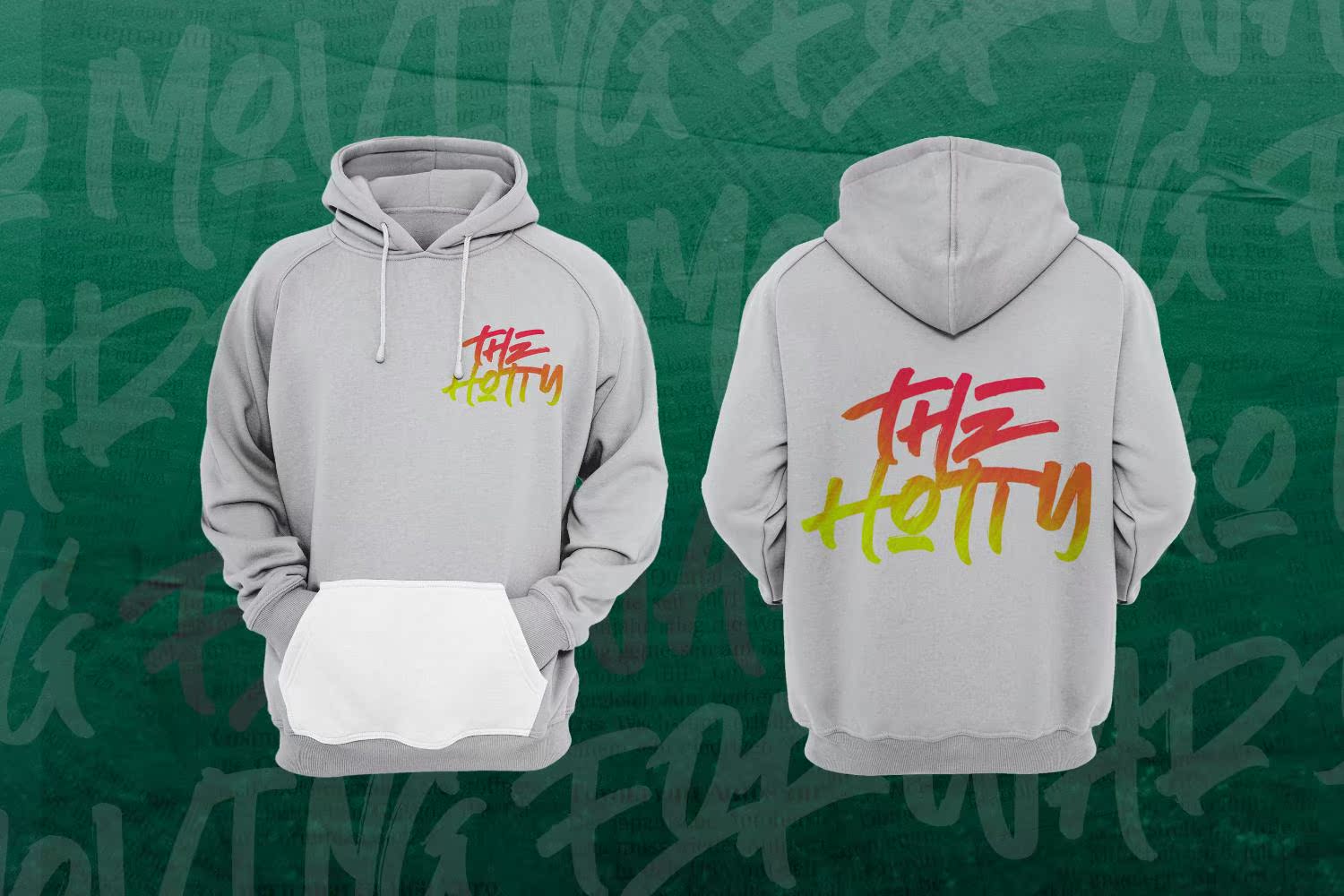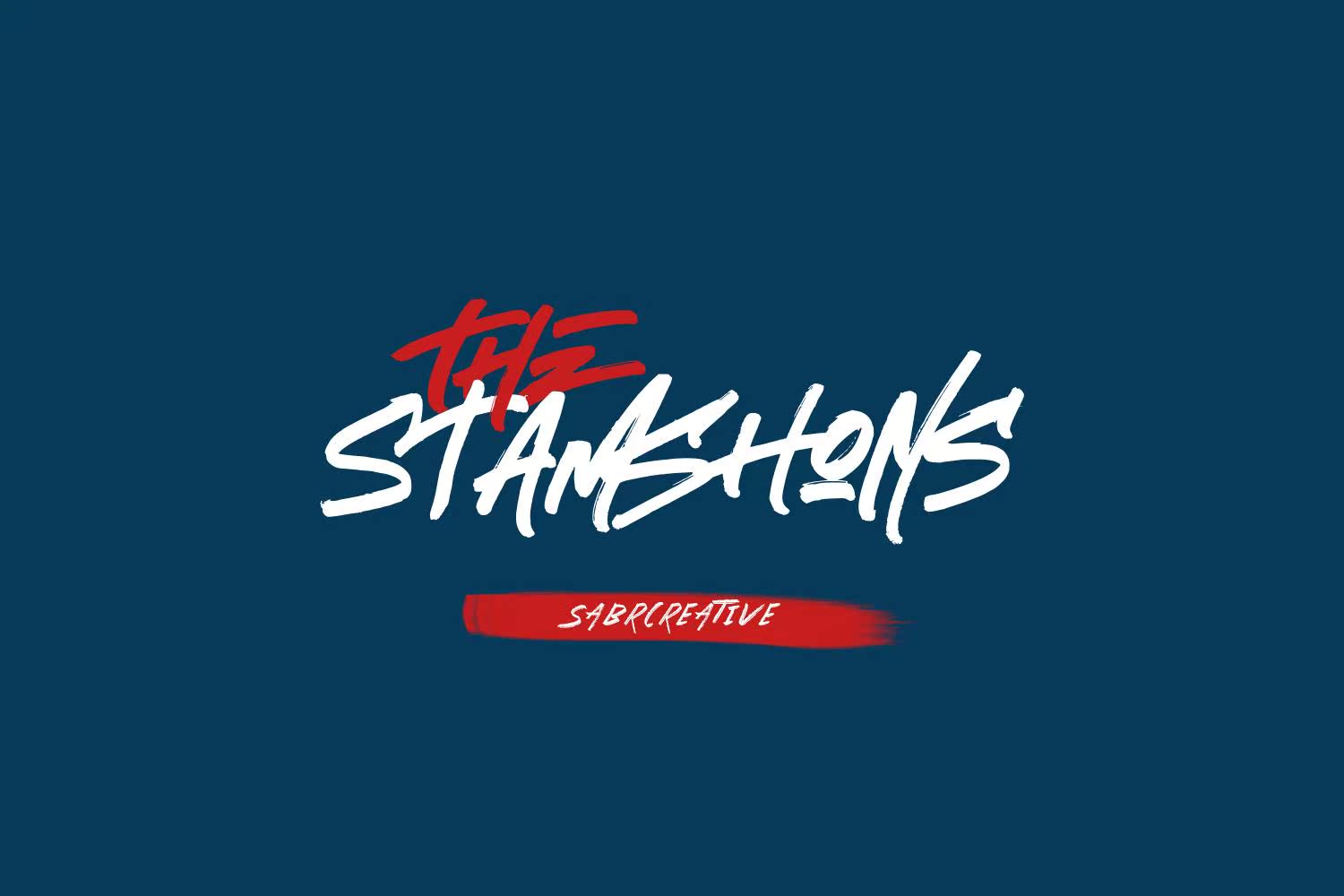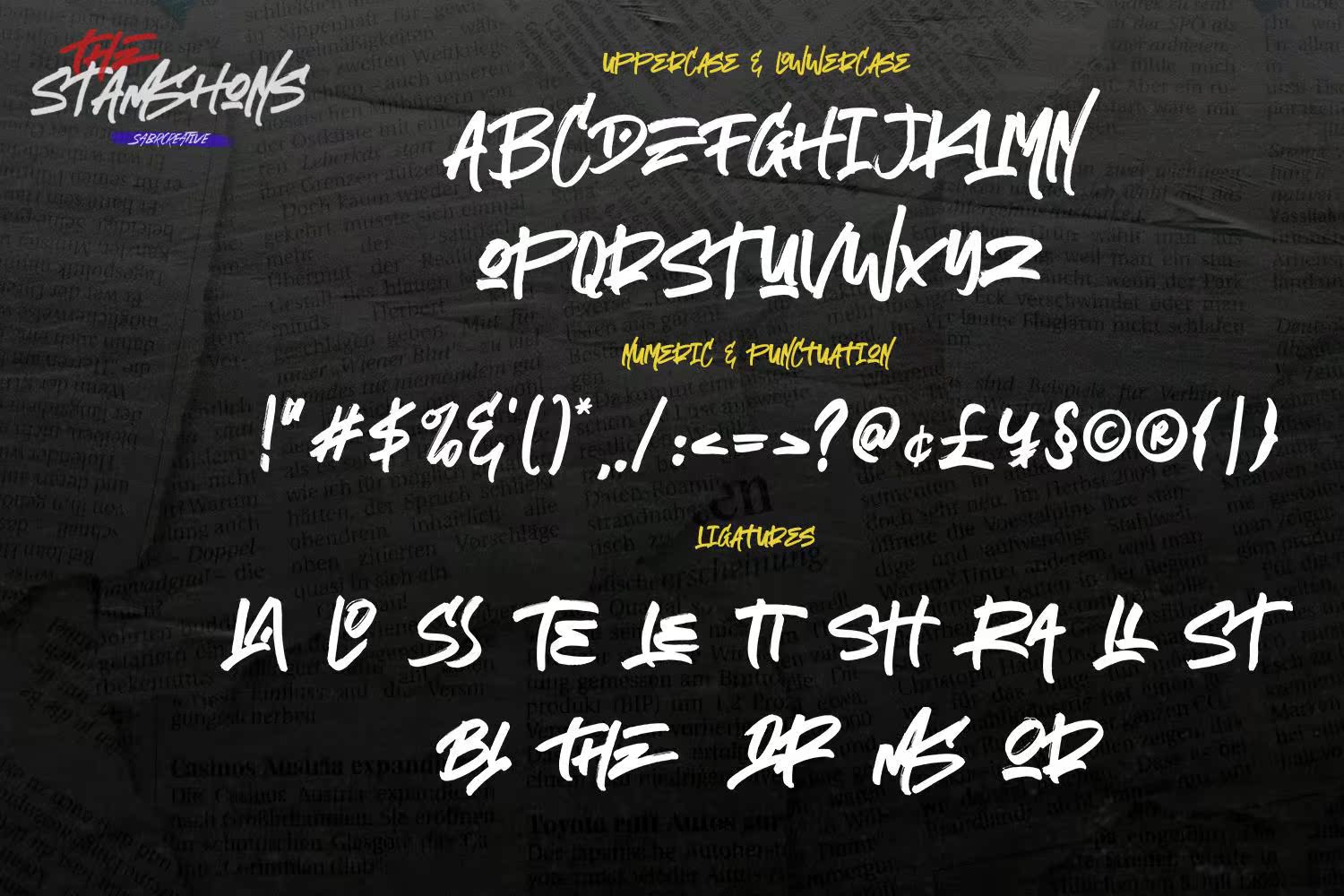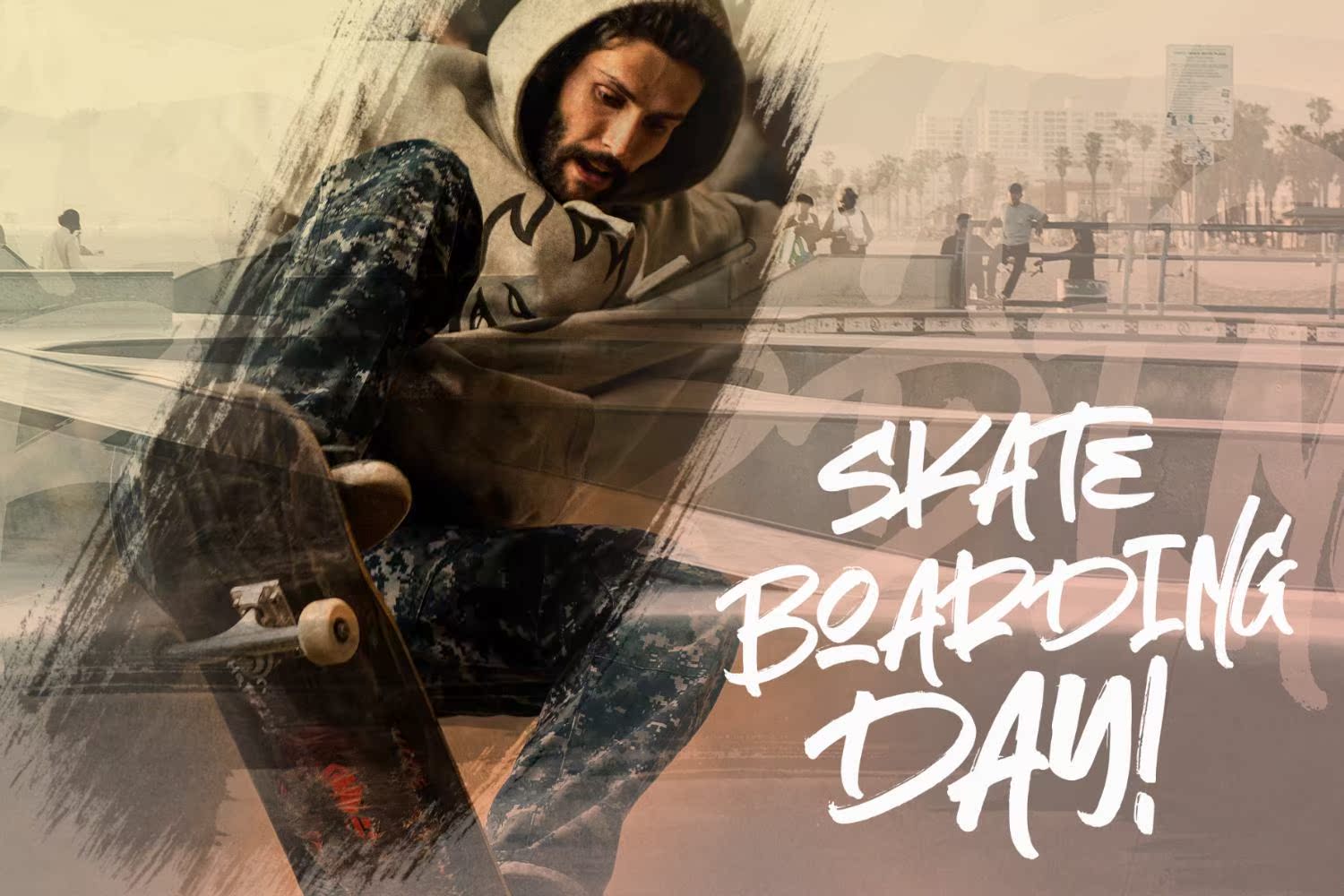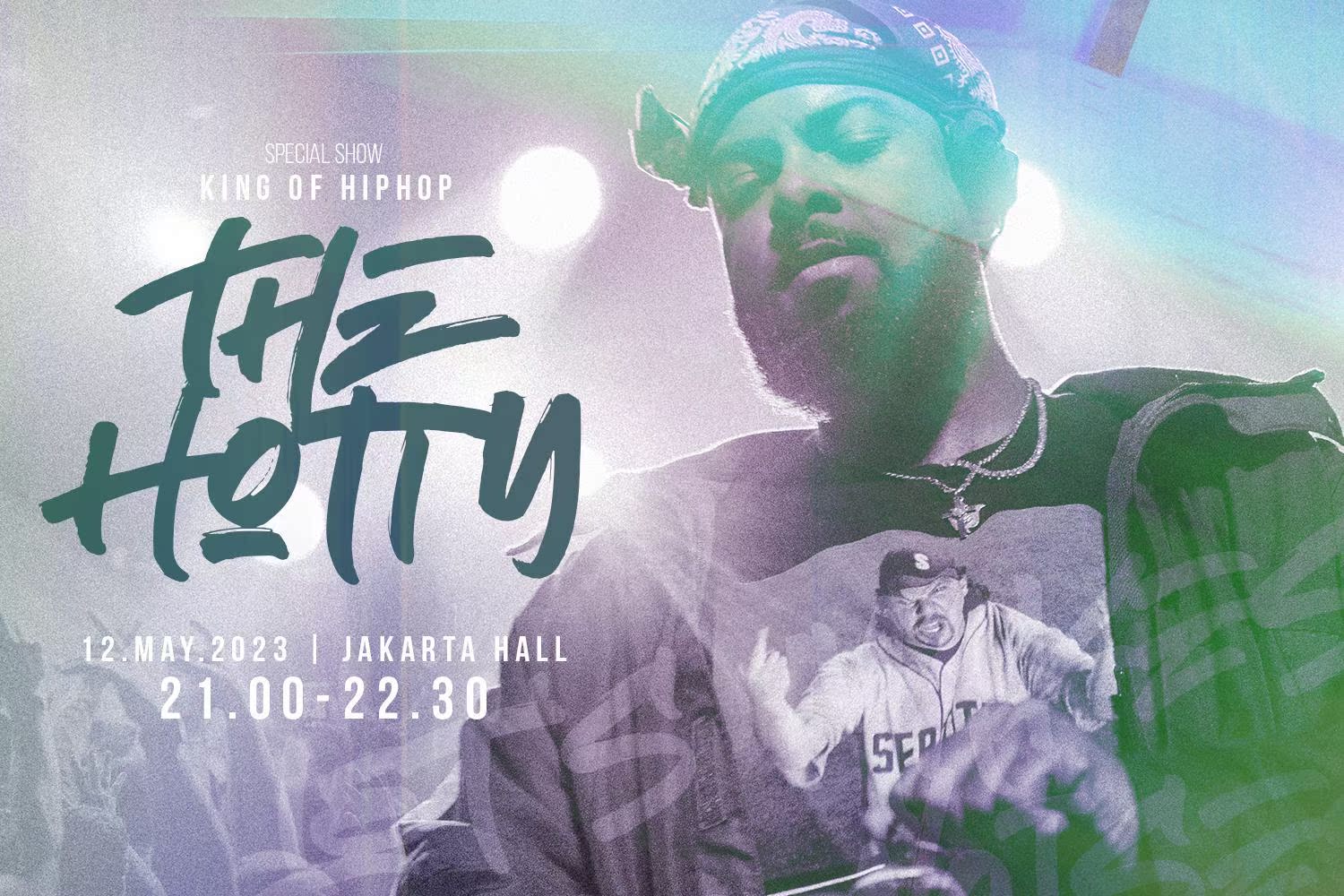
Free the Stamshons Brush Font是一种全新的字体。它适用于您的设计项目,包括T恤、包装、商品、徽标等。因此,此字体是一种多用途字体,您可以在编辑设计信号中使用。它可用于您可以安装任何设备的OTF格式文件。但是,此DemoFont具有个人使用许可证,但如果你想获得更多功能,一定要购买。